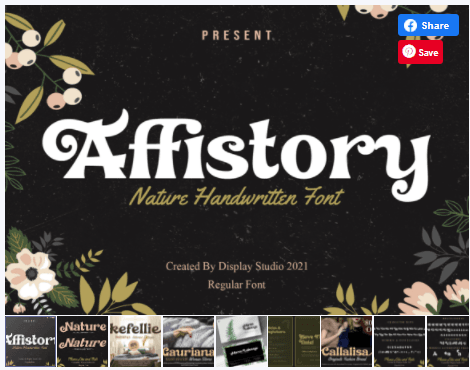
Affistory Font
Affistory - это красивый и стильный рукописный шрифт, который идеально подходит для создания логотипов брендов, приглашений, поздравительных открыток или любого другого проекта, который вы задумали. Добавьте его уверенности в свой творческий дизайн, и он усилит красоту вашей работы! Этот шрифт имеет кодировку PUA, что означает, что вы можете легко получить доступ ко всем глифам и росчеркам!